2023 年 24 種最佳海盜字體(免費和付費)
已發表: 2023-09-15嘿,伙計! 您是一位平面設計師,正在尋找完美的字體來為您的項目進行一次虛張聲勢的改造嗎?
別再猶豫了,因為在今天的博客文章中,我們將深入了解 Google Pirate 字體的世界。 現在,您可能想知道“為什麼要盜版字體?” 好吧,留下來,我會平息你的好奇心。
因此,這篇博文的標題可能引起了您的注意,但您可能想知道盜版字體是否只是一種短暫的趨勢,或者它們是否確實有一些實質內容。
好吧,讓我向您介紹一些有趣的事實。 您是否知道海盜字體可以為任何設計增添一絲冒險和神秘感?
它們具有獨特的魅力,可以瞬間將您的觀眾帶入公海,激發他們的想像力,讓您的作品真正令人難忘。
現在我們已經為史詩般的冒險做好了準備,是時候釋放等待著的寶藏了。 在接下來的部分中,我們將探索各種海盜字體,每種字體都有自己獨特的風格和特徵。
因此,拿起你的指南針,起錨,準備好在排版的海洋中航行,為你的下一個項目尋找完美的海盜風格字體。 嘿,旱鴨子們,讓我們開始這次印刷之旅吧!
最佳優質海盜字體
如果您是一名平面設計師,希望為您的項目添加一絲冒險和虛張聲勢的精神,那麼我們精選的最佳優質盜版字體就是您的最佳選擇。
這些 Adobe Pirate 字體將為您的設計注入活力,並將您的觀眾帶到公海。 所以,帶上你的眼罩,用這些迷人的字體起航吧!
海盜
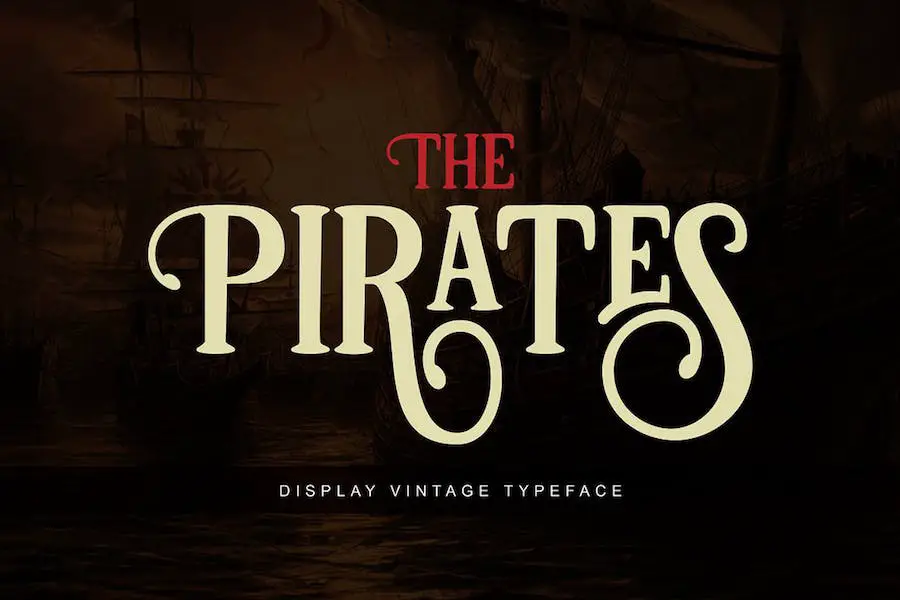
Pirates 是一款令人驚嘆的顯示字體,可為任何設計項目帶來復古、復古和經典的風格。
它不僅限於圖形設計,還可以用於標題、徽章、徽章、婚禮請柬、賀卡等。 該字體輕鬆地將高度復古的感覺與現代 OpenType 功能結合在一起,讓您可以為您的設計創建迷人且和諧的信息。
借助 Canva 的 Pirates 字體,您可以立即將觀眾帶到過去的時代,喚起懷舊之情,並為您的項目增添獨特的魅力。
該字體的經典感覺增添了個性和真實感,使其成為想要創造具有永恆吸引力的設計的設計師的完美選擇。
海盜藍
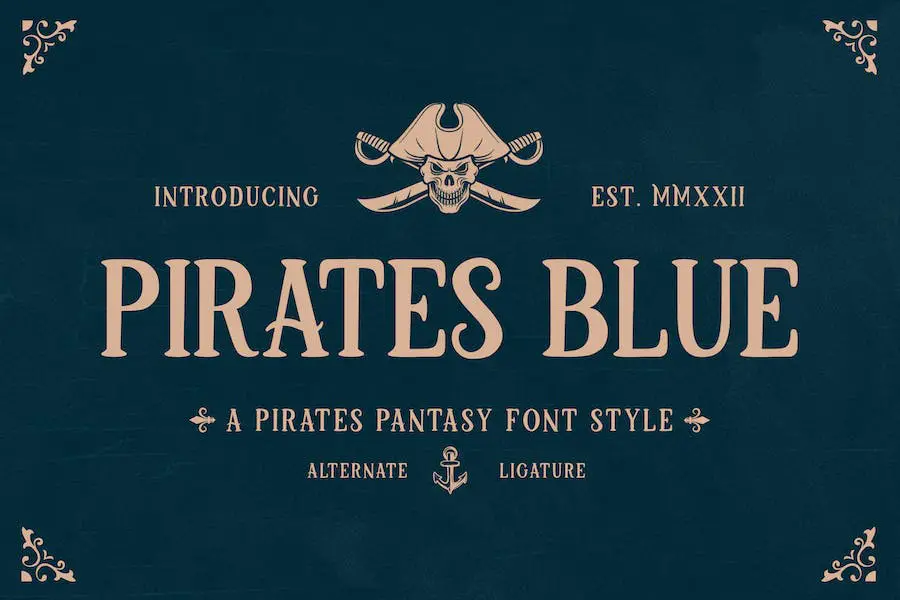
Pirates Blue 是一款海盜奇幻字體,將帶您進入激動人心的冒險。 非常適合在您的項目中營造迷人的氛圍,無論是電影、遊戲還是您想要的任何海盜主題設計。
這款 Cricut 海盜字體捕捉了海盜世界的精髓,並為您的創作增添了一絲刺激。 有了 Pirates Blue,您的設計將充滿冒險和興奮感。
海盜獵人
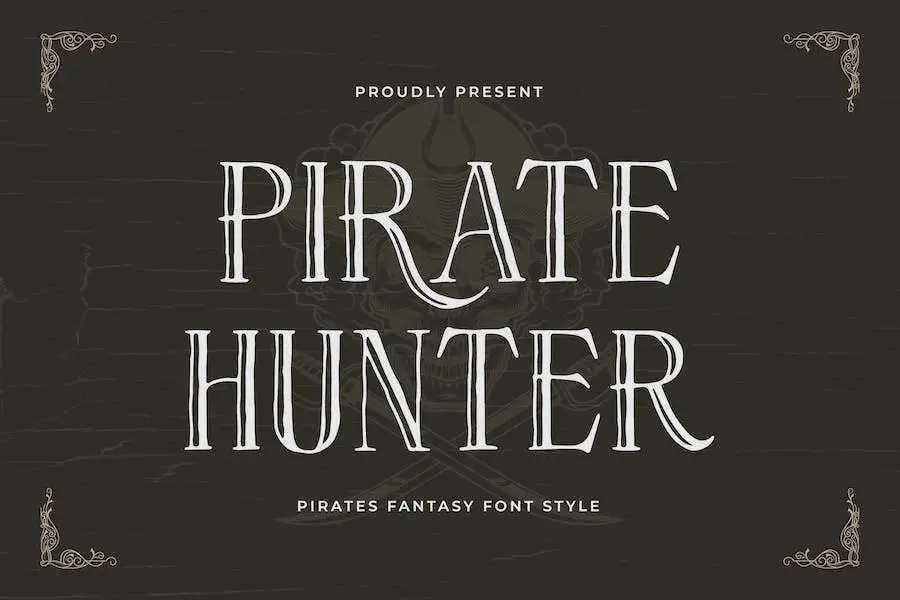
隆重推出 Pirate Hunter,這是一款迷人的海盜主題字體,可立即將您帶入冒險世界。 無論您是在製作電影、遊戲還是任何海盜風格的設計,這款海盜紋身字體都是讓您的項目栩栩如生的完美選擇。
憑藉其多功能的功能,海盜獵人為您提供了創造令人驚嘆的設計所需的一切。 它帶有大寫和小寫字母,以及各種符號和標點符號。 您還可以找到數字、連字和替代字符,為您的作品增添多樣性和獨特性。
用於傳奇設計的海盜字體的突出特點之一是它的多語言支持。 無論您的項目需要什麼語言,這款字體都能滿足您的需求。 告別有限的選擇,擁抱以任何您想要的語言表達自己的自由。
海盜標誌
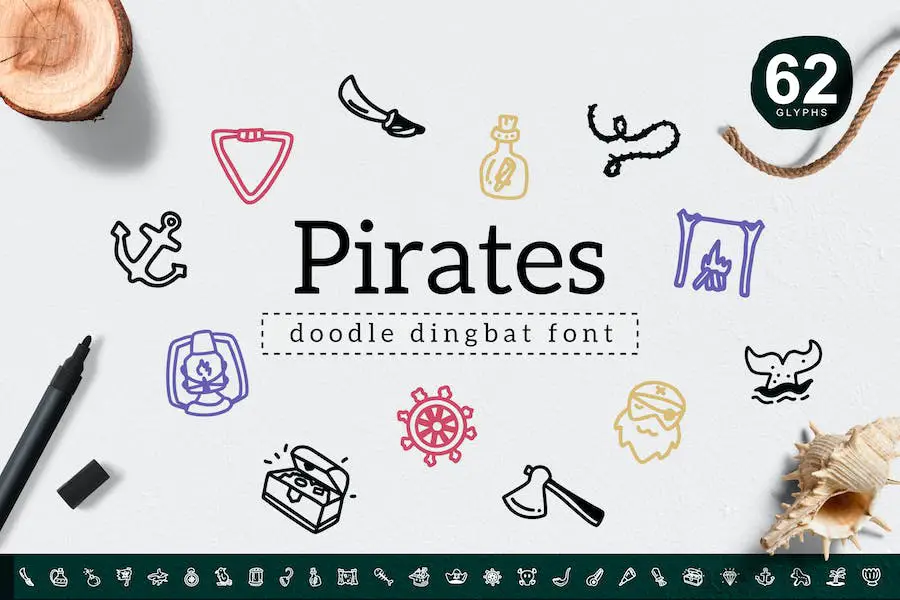
Pirates Dingbat 是一個簡單且用戶友好的海盜主題塗鴉合集。 這款 dingbat 字體有 62 種符號可供選擇,非常適合為各種設計項目(包括徽標和裝飾品)增添冒險色彩。
無論您是在製作海盜主題派對邀請函還是航海徽標,這款 Word 海盜字體都能滿足您的需求。 使用這些有趣且多功能的符號為您的設計帶來大膽的變化。
海盜
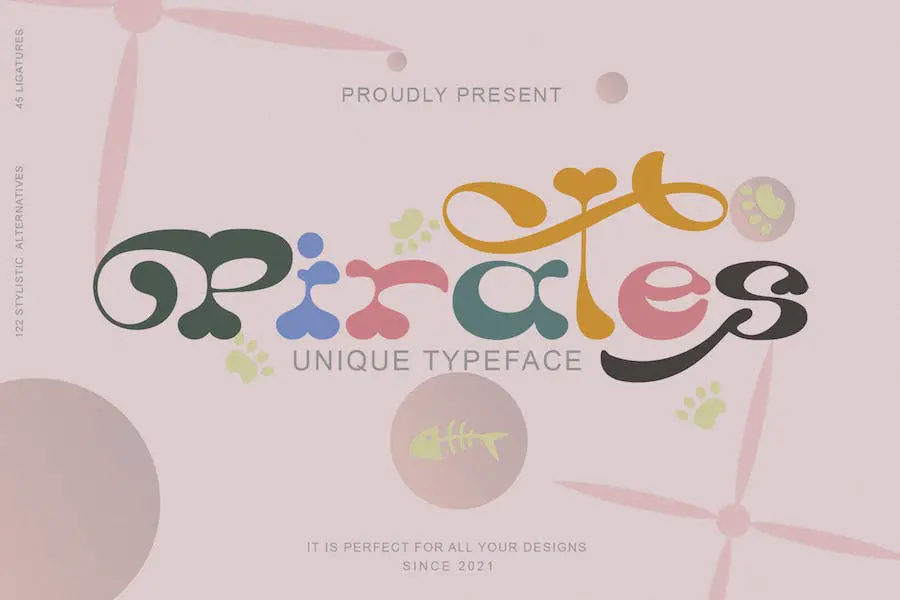
Pirates Font 是一款從 70 年代的設計風格中汲取靈感的字體。 它具有俏皮和時髦的氛圍,為任何項目增添幽默感。 該字體具有一定的美感和獨特性,使其易於記憶和標誌性。
作為字體集合的一部分,海盜字體提供了多功能性,可以應用於各種媒體,其設計理念不過分嚴肅。 其時髦、經典、有趣和獨特的屬性使其適合廣泛的項目。
無論您是在製作復古主題海報、時髦的網站設計還是複古徽標,Pirates Font 都可以輕鬆為您的作品帶來額外的風格和特色。
海盜字體為您的複古設計項目增添了一絲懷舊氣息和熱愛樂趣的精神,與那些尋求獨特且令人難忘的設計的人產生共鳴。
布魯克林海盜
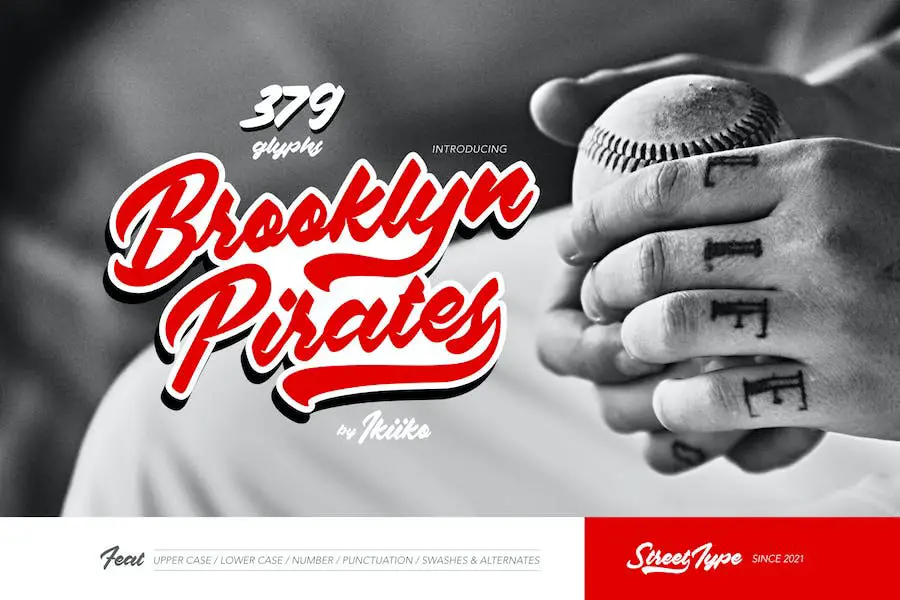
Brooklyn Pirates – 一種為您的設計帶來街頭和城市風格的字體。 這款時髦字體由 ikiikowrk 創建,非常適合徽標、海報、雜誌標題等。
通過各種花飾,您可以根據自己的喜好對其進行定制,並為任何項目增添時尚感。 無論您是創建品牌徽標、設計傳單還是在圖像中添加引言,布魯克林海盜都是完美的選擇。
盜賊
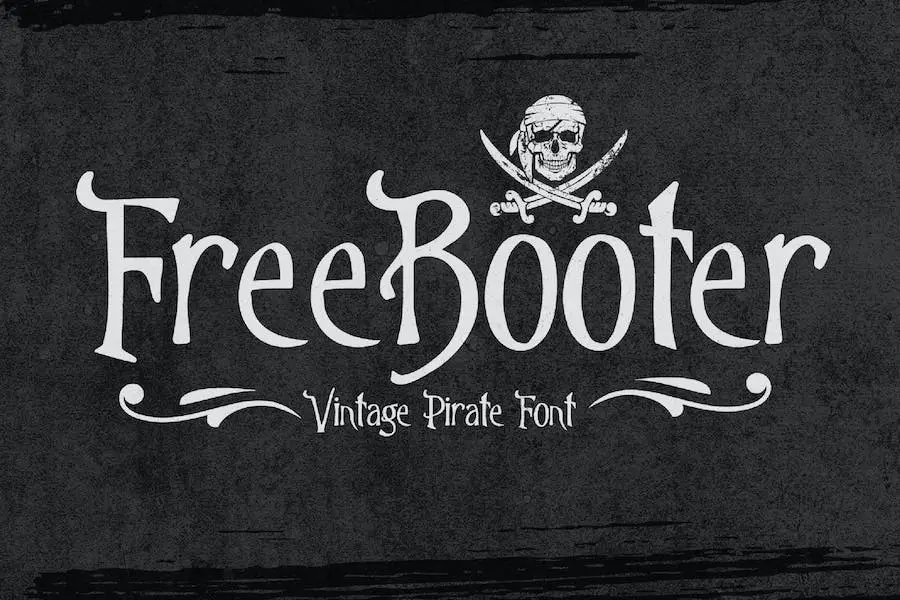
Freebooter 是一款盜版字體,可為您的設計項目帶來 1500 年代的魅力。 其不完美和質樸的風格增添了真實的人情味。
它具有大寫和小寫字母以及特殊字符,非常適合各種創意目的,例如品牌、服裝、社交媒體、廣告、社論和營銷。 使用 Freebooter 為您的設計帶來舊世界的感覺。
海盜崇拜者
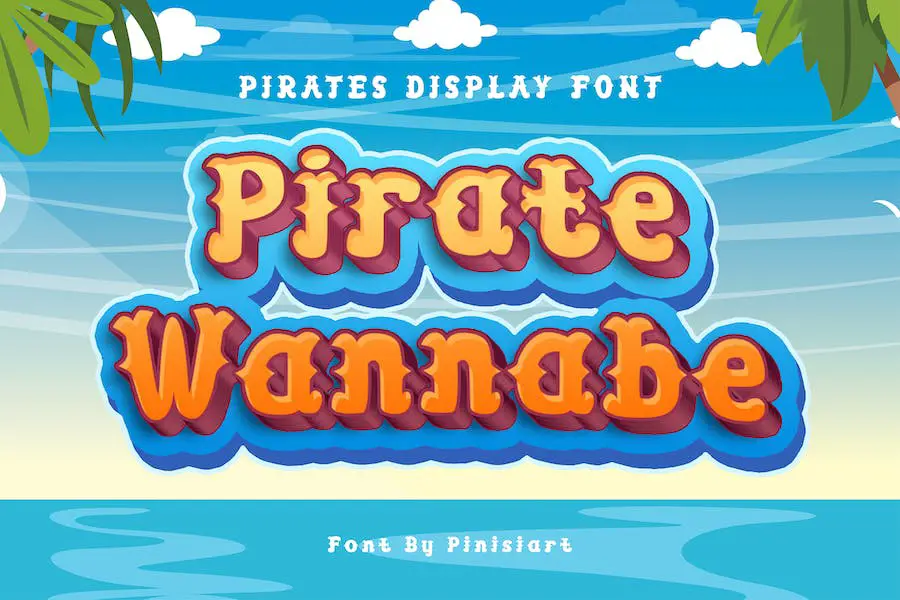
Pirate Wannabe 是一款以其馬刺和經典外觀散發出冒險感和樂趣的字體。 它非常適合具有冒險精神的年輕人,它將使您的設計在人群中脫穎而出。
無論您是在創建雜誌、海報、電影標題、音樂海報,甚至是 YouTube 封面和縮略圖,這種字體都會為您的項目增添可愛俏皮的氛圍。
對於那些希望為自己的設計增添一絲童年懷舊和興奮的人來說,這種字體是一個不錯的選擇。
想像一下將它用於兒童雜誌封面或電影海報來進行一場虛張聲勢的冒險。 這種字體的多功能性使其適合各種創意項目。
Pirate Wannabe 的與眾不同之處在於它能夠為任何設計帶來歡樂和俏皮感。 它就像一個創造力的寶庫,為您的項目增添一絲興奮。 那麼,為什麼不釋放你內心的海盜,讓你的想像力盡情發揮這種令人愉快的字體呢?
海盜朗姆酒
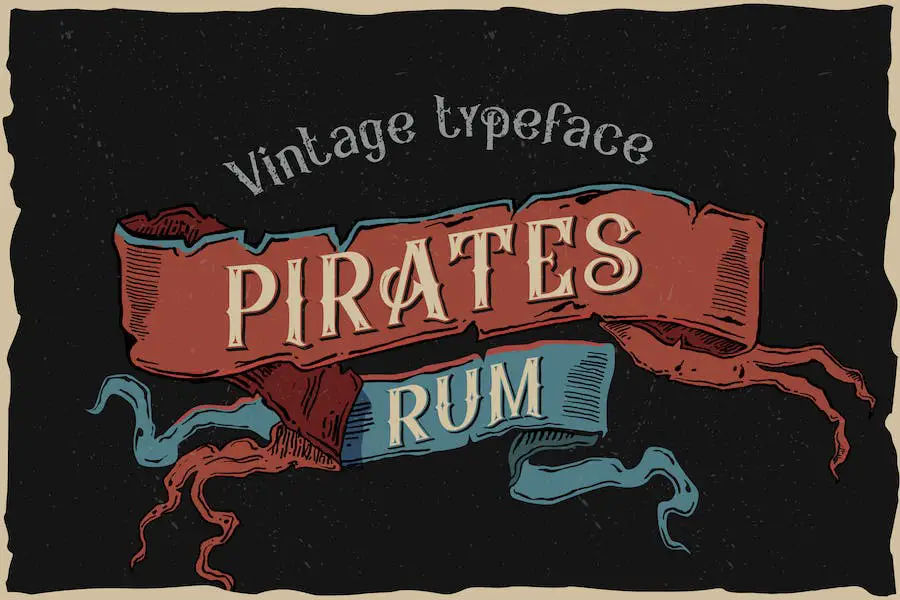
Pirates Rum 是一種多功能字體,提供一系列功能來增強您的設計項目。 憑藉其無襯線風格,它為您的文本帶來現代和時尚的外觀。 字母間距均衡,確保任何大小的清晰易讀性。
該字體屬於網絡字體分類,這意味著它針對在線使用進行了優化,並且可以在各種設備和瀏覽器上完美顯示。 無論您是為網站還是社交媒體帖子進行設計,Pirates Rum 都是可靠的選擇。
海盜朗姆酒的突出特點之一是其尺寸的靈活性。 它可以調整為任何尺寸,而不會失去其清晰度或質量。 這使得它在為您的設計創建不同元素(從標題到正文)時非常有用。
海盜
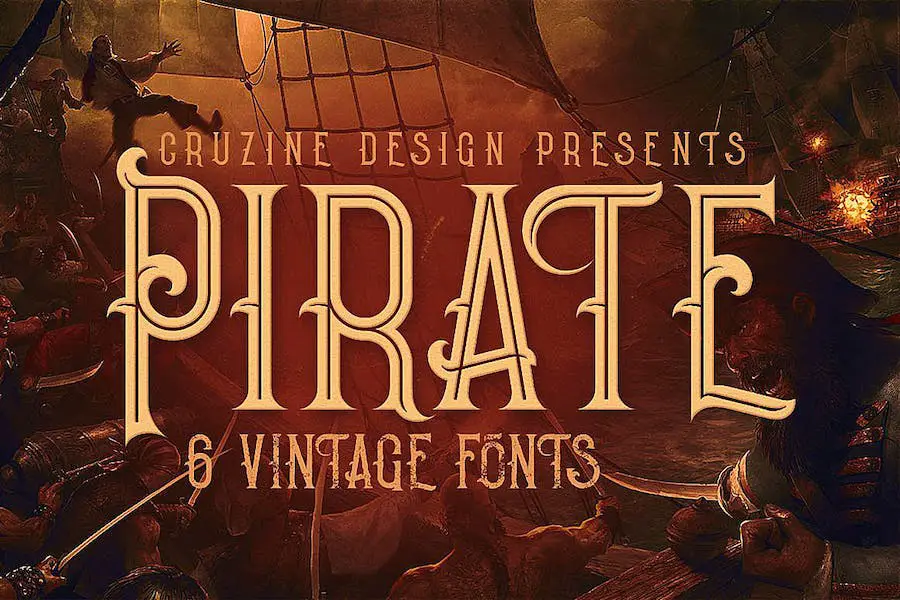
Pirate 是一種獨一無二的複古或複古風格的自定義襯線字體,可為您的設計項目帶來獨特的觸感。 憑藉 6 種不同的風格(常規、垃圾、內聯、內聯垃圾、陰影和陰影垃圾),您有無限的可能性為您的作品增添個性和魅力。
無論您的目標是海盜主題設計還是希望給您的項目帶來復古氛圍,Pirate 都是您需要的字體。
海盜字體的常規風格散發著優雅和傳統,而垃圾風格則增添了粗獷和前衛的外觀。
內聯風格提供時尚和精緻的觸感,而內聯垃圾風格則增添了破舊和復古的感覺。 陰影樣式為文本提供深度和尺寸,陰影垃圾樣式賦予文本質樸和風化的外觀。
麥哲倫
Magellan 是一種粗糙且飽經風霜的字體,捕捉了海盜傳說和尋寶的精髓。 每個字母都帶有神秘感和興奮感,非常適合創建引人注目的標題、標牌、活動海報等。
讓自己沉浸在麥哲倫的海盜世界中,因為它為您的設計項目增添了真實感和冒險氣息。 無論您是從事主題派對、遊戲設計還是品牌推廣,這種獨特的字體都會讓您的設計脫穎而出。
與 Magellan 一起踏上虛張聲勢的冒險之旅——一種海盜顯示字體,可為您的設計帶來公海精神。
羅莎蒙
Rosamone 是一款令人興奮的海盜奇幻字體,讓您沉浸在驚心動魄的冒險中。 該字體提供廣泛的功能,非常適合遊戲、電影或海盜主題設計。
它包括大寫和小寫字母、符號和標點符號、數字、連字、替代符號和多語言支持。 讓您的創造力與 Rosamone 一起航行,將您的設計變為現實。
海盜旗
Jolly Roger 是一款海盜奇幻字體,將帶您進入冒險世界。 該字體非常適合電影、遊戲和海盜主題設計,具有大寫和小寫字母、符號和標點符號、數字、連字、替代符號和多語言支持。
憑藉其獨特的風格,Jolly Roger 非常適合為您的項目增添一抹虛張聲勢的魅力。
傑克骷髏
Jack Skull 是一款海盜奇幻字體,讓您沉浸在激動人心的冒險中。 它非常適合創建迷人的電影、遊戲和海盜主題設計。
憑藉其大寫和小寫字母、符號和標點符號、數字、連字、替代和多語言支持,該字體提供了使您的項目栩栩如生所需的所有功能。
黑旗
Black Flag 是一款海盜奇幻字體,可立即將您帶入冒險氛圍中。 這種字體選擇非常適合電影、遊戲和海盜主題設計,將以其虛張聲勢的魅力增強您的項目。
Black Flag 具有多語言支持和替代數字功能,用途廣泛,可供廣大設計師使用。
其大寫字符、符號和標點符號為您的作品帶來真實的海盜感覺,而小寫連字則增添了一絲優雅和個性。
無論您是在創建徽標、海報還是網站,Black Flag 都會增添額外的興奮感和創造力,從而吸引您的受眾。 告別無聊和通用的字體,讓 Black Flag 在您的設計項目中起航。
舍伍德
Sherwood 是一款令人印象深刻的海盜奇幻字體,可立即將您帶入驚心動魄的冒險世界。
該字體非常適合創建迷人的電影、遊戲和海盜主題設計,提供多種功能,包括大寫和小寫字母、符號和標點符號、數字、連字、替代字符和多語言支持。
憑藉其多功能的功能,Sherwood 一定會提升您的項目並將您的想像力變為現實。
最好的免費海盜字體
希望為您的設計項目增添一些虛張聲勢的魅力? 別再猶豫了! 在本節中,我們收集了最好的免費海盜字體,它們將為您的設計帶來完美的航海風格。
嘗試一下這些字體,看看它們如何增強您的下一次創意工作。 是時候開始一場印刷冒險了!
骨頭
Bones 是一款專為尋求增強項目設計的圖形設計師設計的字體。 該字體由 junkohanhero 創建,免費供個人使用。
借助 Bones,設計師可以使用獨特且引人注目的字體,為他們的設計增添一絲個性。 它非常適合需要大膽和前衛美學的項目。
憑藉簡潔的線條和獨特的曲線,Bones 在同類字體中脫穎而出。 設計中對細節的關注確保每個角色都具有視覺衝擊力,並為任何設計增添了吸引力的元素。
克斯博內斯
Xbones 是由 Iconian Fonts 創建的捐贈軟件字體。 它為希望增強其項目的圖形設計師提供了獨特而時尚的選擇。
憑藉其海盜主題的設計,Xbones 為任何設計增添了俏皮和冒險的氣息。 字體非常詳細,每個字符都經過精心製作,類似於骷髏和交叉骨。
無論您是在從事海盜主題項目,還是只是想為您的設計增添一絲鋒芒,Xbones 都是完美的選擇。
結論
為了回顧我們在本文中討論的內容,我們探索了盜版字體的世界以及它們如何增強您的圖形設計項目。 我們深入研究了海盜字體的不同風格、它們的獨特特徵,以及它們如何為您的設計添加冒險和陰謀的感覺。